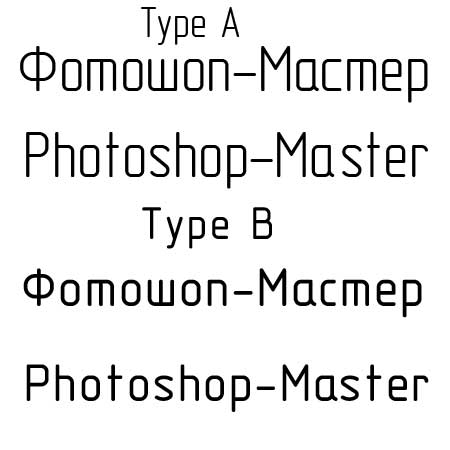
эх, жалко что когда нам задавали такой шрифт чертить мне в голову не пришло поискать такой сайт)))
Отличный шрифт для учителей черчения. Спасибо!
Очень полезный шрифт для инженерной специальности. Спасибо большое)))
Супер! Увидел этот шрифт и сразу появилась идея для сайта!!